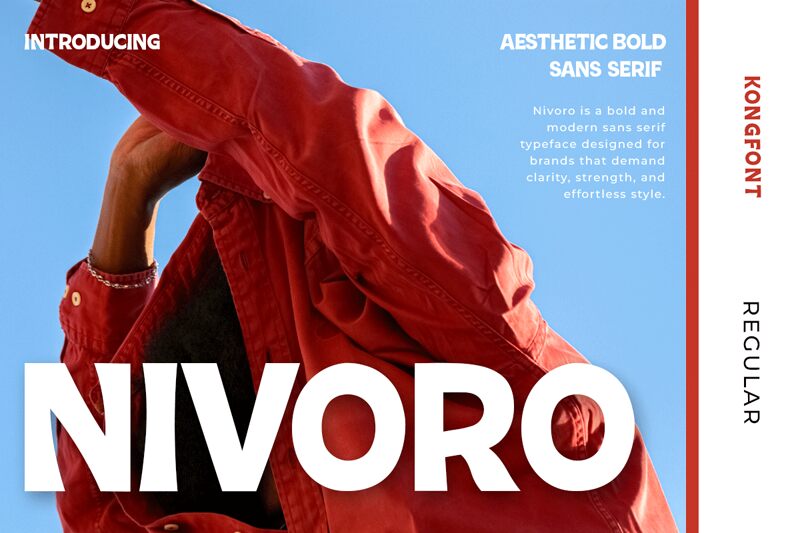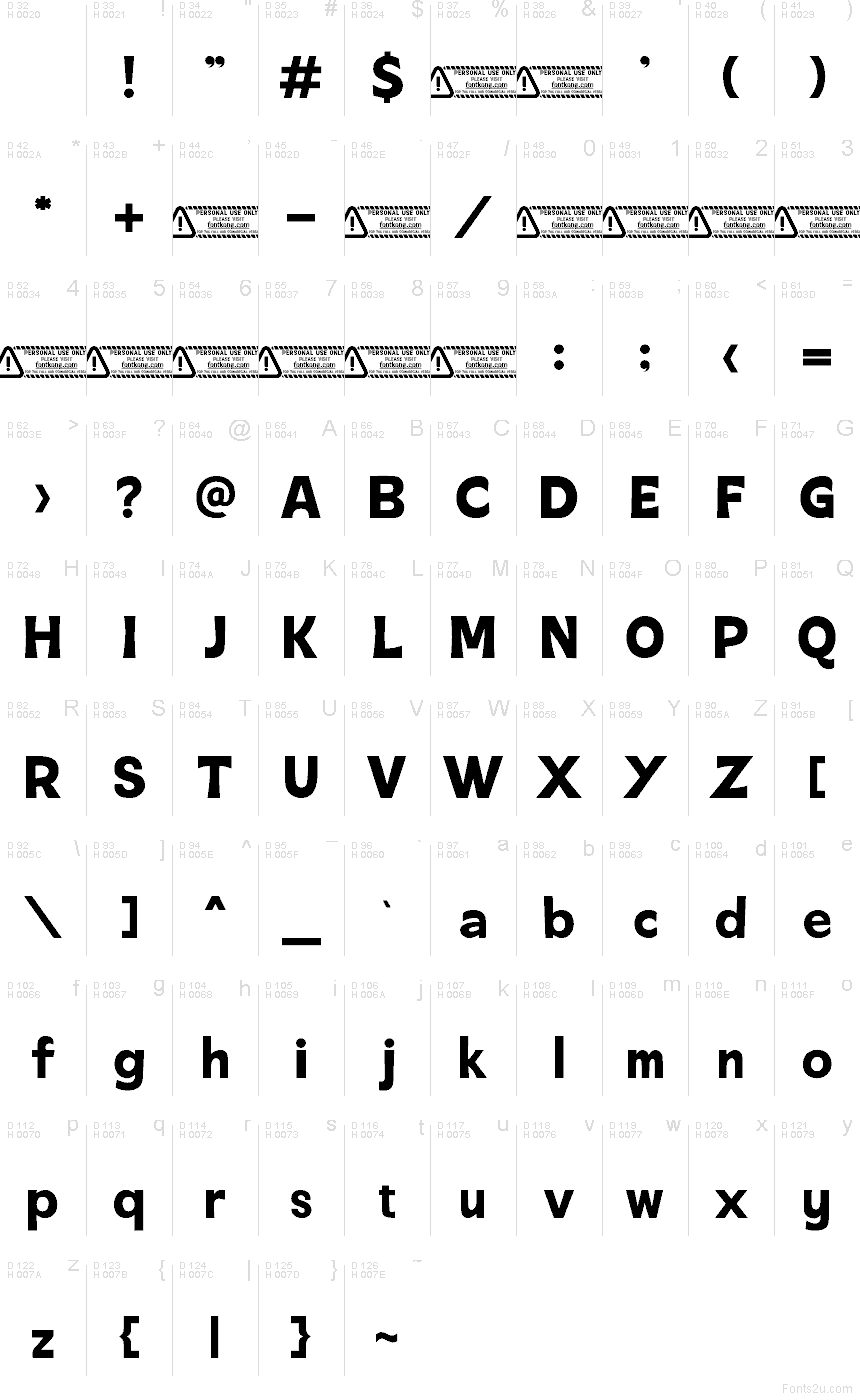
Písmo Nivoro od Kong Font je bezplatný font typu display so širokými, zaoblenými tvarmi písmen a jednoduchou geometrickou štruktúrou. Písmená pôsobia stabilne a priamočiaro, s plynulými krivkami a kompaktnými spojmi, ktoré dodávajú názvu pevný grafický vzhľad.
Nivoro skvele funguje v logách, nadpisoch na plagátoch, obaloch, grafikách pre sociálne siete a banneroch akcií, kde na výraznom tvare písmen záleží viac než na dlhom čítaní. Tento bezplatný font sa hodí aj pre značky a krátke redakčné texty, pretože jeho čisté a vyvážené tvary držia dobre pokope v krátkych textoch s vysokým dopadom.